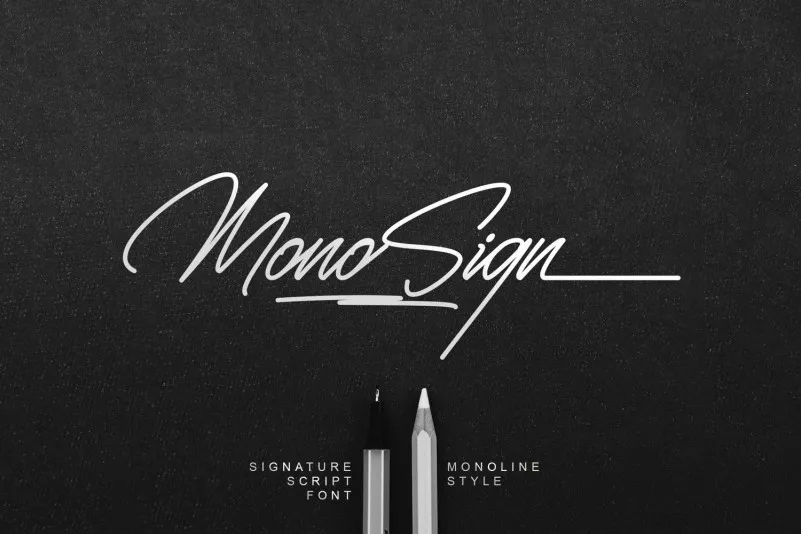
A Monosign Font é uma escolha perfeita para quem busca um estilo script limpo e natural. Desenvolvida por lemonthe, essa fonte é projetada para ser usada puramente à mão, mantendo características únicas e verdadeiras. Suas linhas suaves e elegantes se adaptam a diversos tipos de projeto, como logos e marcações, convites e materiais de correspondência, designs para casamentos, postagens nas redes sociais, anúncios, embalagens de produtos, design dos próprios produtos, etiquetas, fotografia e até mesmo marcas de água. O fato de ser PUA codificado significa que você pode acessar facilmente todos os caracteres e swashes desta fonte, tornando o processo de criação mais agradável e eficiente. Ideal tanto para iniciantes quanto para profissionais, a Monosign Font é uma opção perfeita para aqueles que buscam um toque natural em seus projetos visuais.